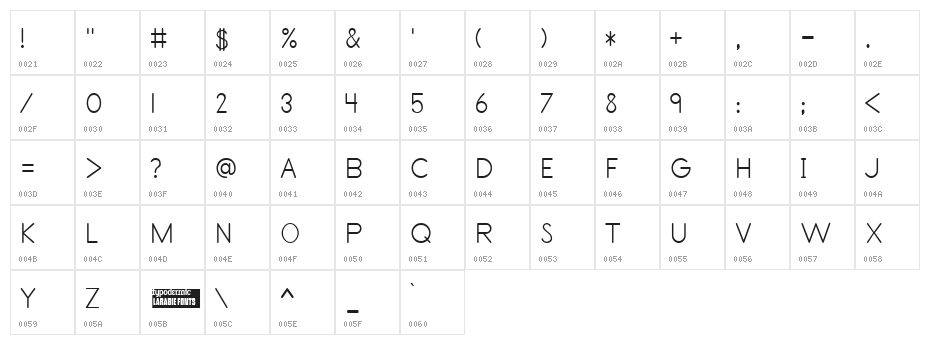
Primer Print Font
| Область применения | Headlines, Body text, Logos |
| Рекомендуемые проекты | Ideal for educational materials, children's books, signage, and user interfaces due to its clarity and simplicity. |